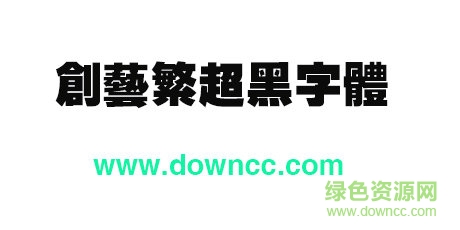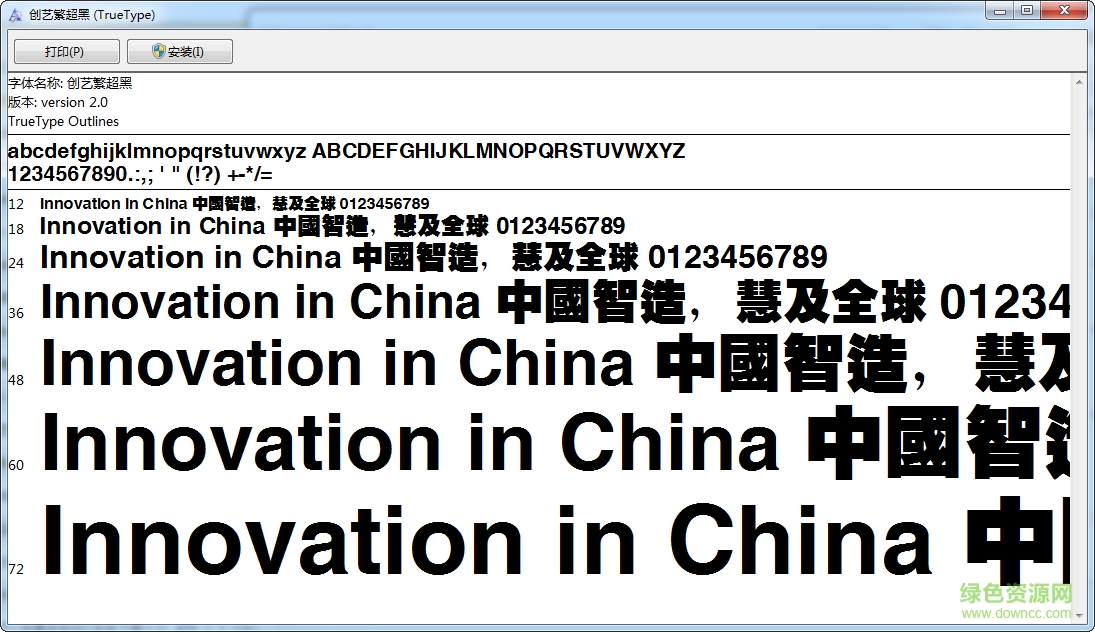
ctchaoheisf字體又叫創(chuàng)藝繁超黑字體,是一款超級粗黑的創(chuàng)藝字體,外形粗獷樸素異常醒目,用作廣告字體logo或宣傳標語非常適合,其設計詞句也非常的具有特色亮點,適合廣大朋友們使用,需要的用戶歡迎來本站免費下載!
保持著黑體字的共有特點,筆畫粗壯有力,橫豎筆畫粗細比較接近, 兩端平直,加鋒較小,筆畫簡潔粗壯,厚實有力
黑體字又稱方體或等線體,是一種字面呈正方形的粗壯字體,字形端莊,筆畫橫平豎直,筆跡全部一樣粗細,結(jié)構醒目嚴密。黑體適用于標題或需要引起注意的醒目按語或批注,因為字體過于粗壯,所以不適用于排印正文部分。